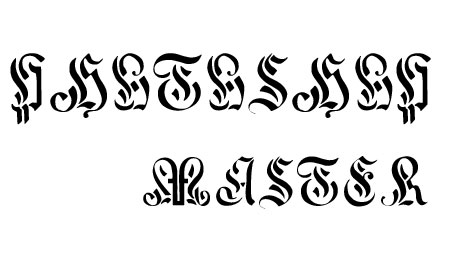
Шрифт - Curved Manuscript, 17th c
Красивый шрифт, с буквами в стиле древнего манускрипта, без поддержки русского языка
а мне так нравится..загадочный )
красивый ,плохо читаемый шрифт(
Плохо читаем(